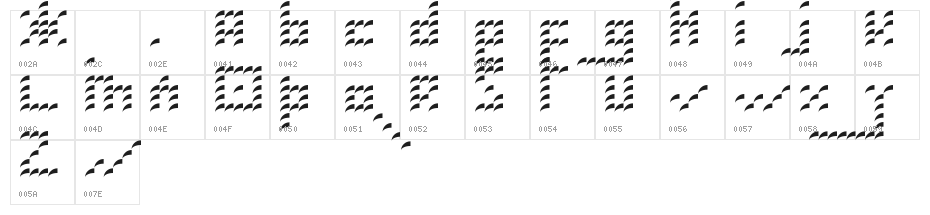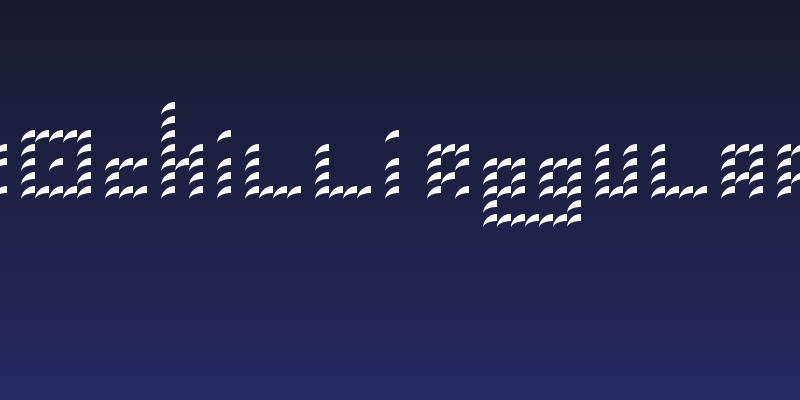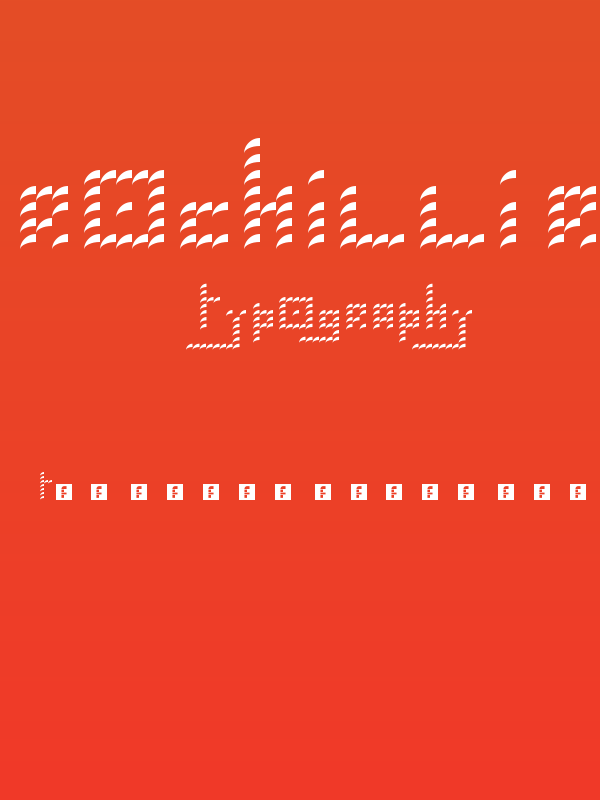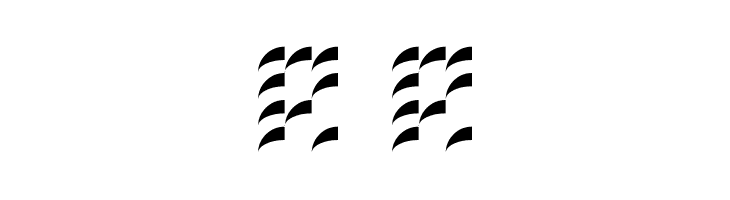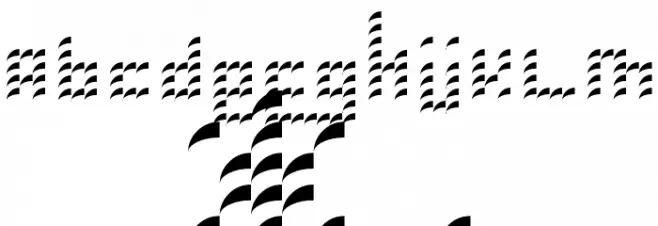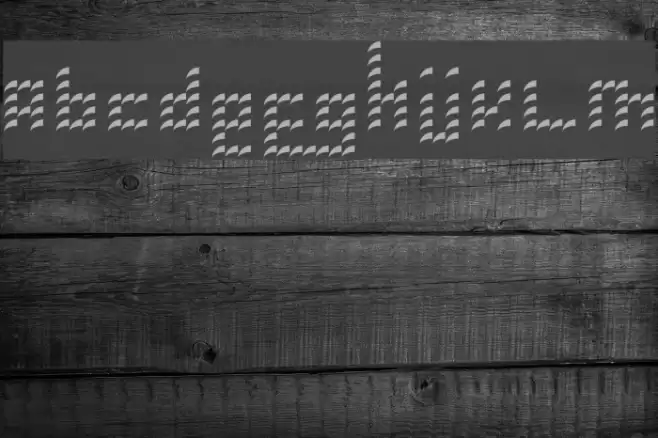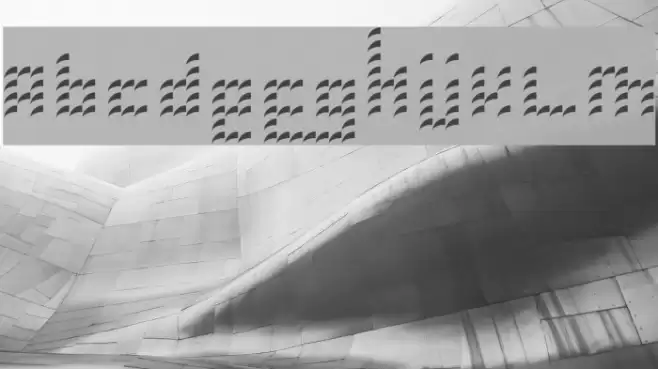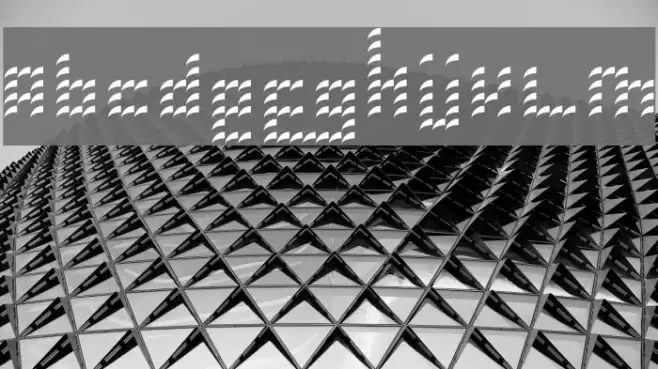
Rochilli Regular Font
| Anwendungsfall | Logos, Headlines, Posters |
| Vorgeschlagene Projekte | Ideal for creative projects such as posters, album covers, and branding that require a bold and artistic touch. |